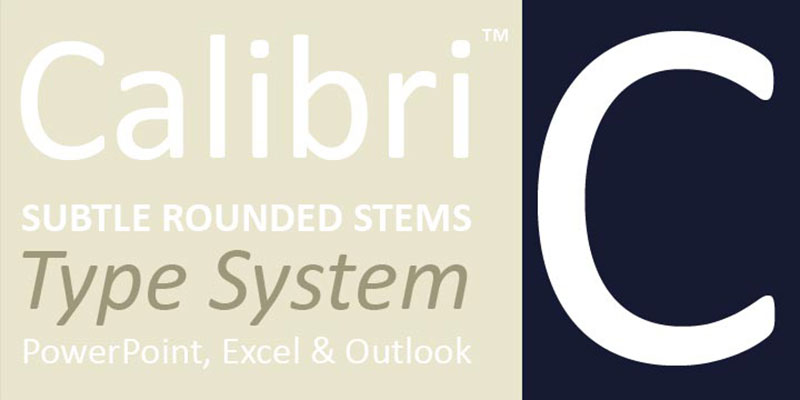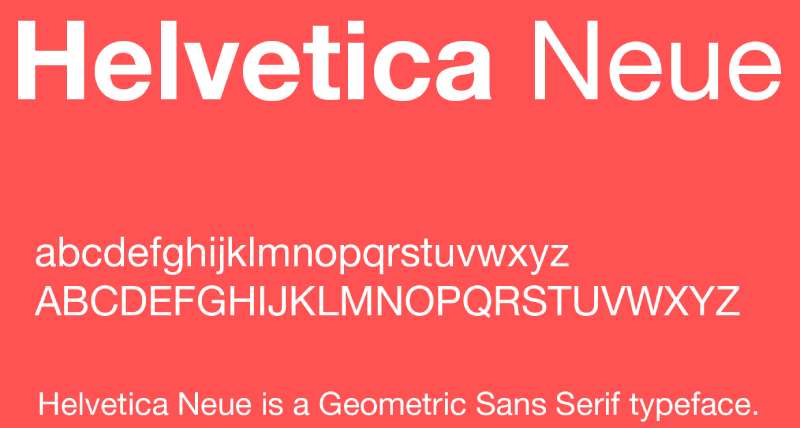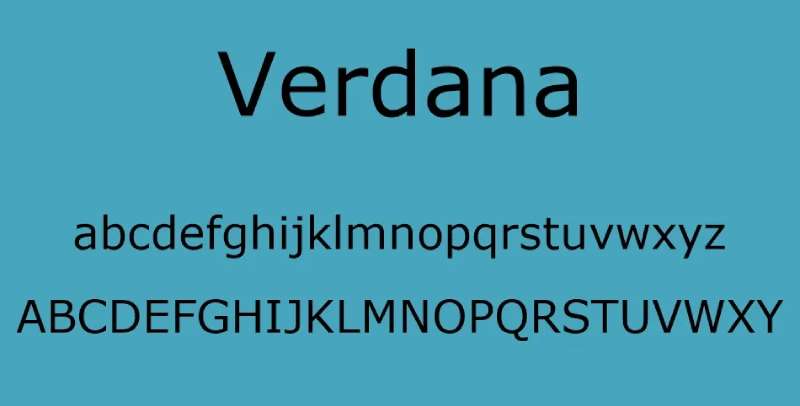
Stellen Sie sich das vor: Sie haben einen Lebenslauf erstellt, der ein Meisterwerk Ihrer Leistungen ist, aber Moment, schreit die Schriftart ‚professionell‘ oder ‚meh‘? Tauchen wir ein in die Welt der besten Schriftarten für Lebensläufe.
Warum? Weil die Schriftart, die Sie wählen, der Anzug ist, den Ihre Worte vor Ihrem zukünftigen Chef tragen. Es geht nicht nur darum, gut auszusehen; es geht darum, diese Worte für Sie arbeiten zu lassen.
In diesem Artikel werden wir die Magie hinter der Auswahl der perfekten Schriftart enthüllen. Es geht nicht nur um Arial gegen Times New Roman.
Es geht um Typografie, die Professionalität vermittelt, Lesbarkeit der Schriftart, die die Augen des Personalvermittlers durch Ihre Fähigkeiten gleiten lässt, und Schriftstile, die Ihre Persönlichkeit widerspiegeln.
Wir führen Sie durch das Labyrinth der digitalen Kompatibilität, stellen sicher, dass Ihr Lebenslauf auf jedem Bildschirm glänzt, und helfen Ihnen, die ATS-freundlichen Wege zu navigieren.
Am Ende haben Sie ein Toolkit aus Serif- und Sans-Serif-Schriftarten, das Kreativität mit Professionalität ausbalanciert.
Sie lernen, wie man Schriftarten für eine visuelle Hierarchie paart, die Schriftgröße für Wirkung anpasst und sicherstellt, dass die Schriftart Ihres Lebenslaufs Personalchef-freundlich ist. Bereit, jeden Buchstaben zu zählen?
Die besten Schriftarten für Lebensläufe
| Schriftartname | Serif/Sans-serif | Lesbarkeit | Professionalität | Häufig verwendet | Einzigartigkeit |
|---|---|---|---|---|---|
| Times New Roman | Serif | Hoch | Sehr hoch | Niedrig |
| Cambria | Serif | Hoch | Hoch | Hoch | Mittel |
| Georgia | Serif | Hoch | Hoch | Mittel | Mittel |
| Garamond | Serif | Hoch | Hoch | Mittel | Hoch |
| Didot | Serif | Mittel | Niedrig | Hoch |
| Book Antiqua | Serif | Hoch | Hoch | Niedrig | Hoch |
| Baskerville | Serif | Hoch | Hoch | Niedrig | Mittel |
| Century Schoolbook | Serif | Hoch | Hoch | Niedrig | Mittel |
| Arial | Sans-serif | Hoch | Mittel | Sehr hoch | Niedrig |
| Calibri | Sans-serif | Hoch | Hoch | Sehr hoch | Niedrig |
| Helvetica | Sans-serif | Hoch | Hoch | Hoch | Niedrig |
| Verdana | Sans-serif | Hoch | Mittel | Hoch | Niedrig |
| Lato | Sans-serif | Hoch | Mittel | Mittel |
| Trebuchet MS | Sans-serif | Hoch | Mittel | Mittel |
| Gill Sans | Sans-serif | Hoch | Mittel | Niedrig | Hoch |
| Futura | Sans-serif | Mittel | Niedrig | Hoch |
| Tahoma | Sans-serif | Hoch | Mittel | Mittel |
Serif-Schriftarten
Hallo! Lassen Sie uns in die Welt der Serifenschriftarten eintauchen, ein Reich, in dem jeder Buchstabe ein wenig mehr Flair bekommt. Wir sprechen über diese kleinen Füße an den Enden der Buchstaben.
Sie sind nicht nur zur Show; sie verleihen Ihrem Lebenslauf ein klassisches, poliertes Aussehen. In einem Stapel von tausend wollen Sie, dass Ihrer flüstert: „Ich bin der Richtige“, oder?
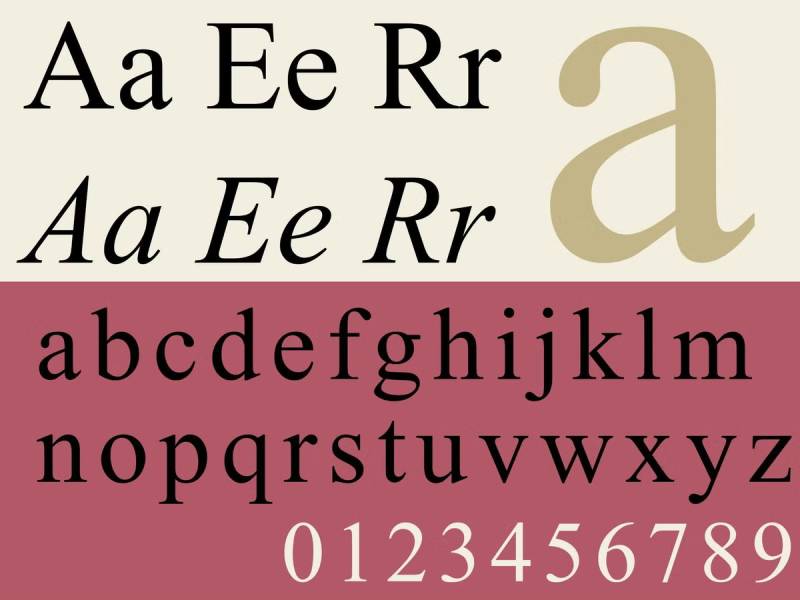
Das mag altmodisch klingen, aber es ist wie das zeitlose kleine schwarze Kleid – es funktioniert einfach. Perfekt, wenn Sie es professionell und lesbar halten wollen. Hier können Sie nichts falsch machen, besonders in formellen Bereichen wie Recht oder Akademie.
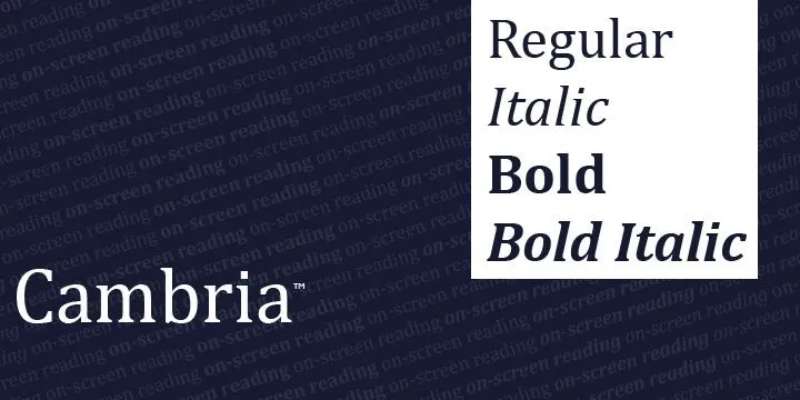
Es ist wie der moderne Cousin von Times New Roman. Speziell für das Lesen auf dem Bildschirm entwickelt, ist seine Lesbarkeit top. Ideal, wenn Ihr Lebenslauf eher auf einem Bildschirm als auf Papier gelesen wird.
Es hat diese warme, einladende Atmosphäre. Seine Buchstaben sind etwas breiter, was es super lesefreundlich macht. Plus, es sieht auf jedem Gerät großartig aus, dank seiner starken digitalen Kompatibilität.
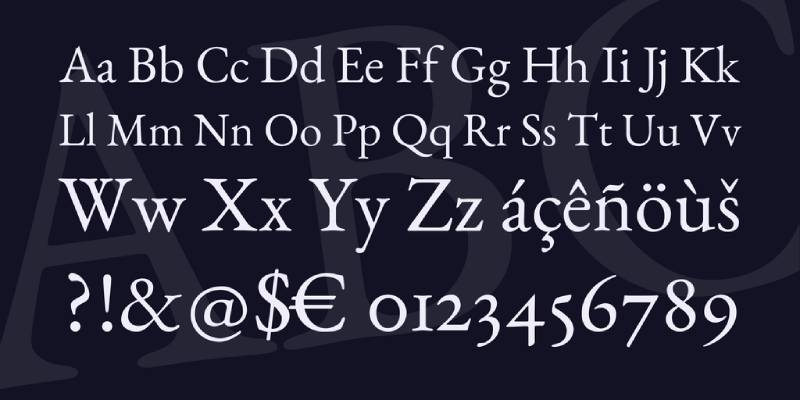
Oh, Garamond – elegant, raffiniert, ein Hauch von altweltlichem Charme. Für diejenigen, die auffallen möchten, aber auf subtile, „Ich habe Klasse“-Art und Weise.
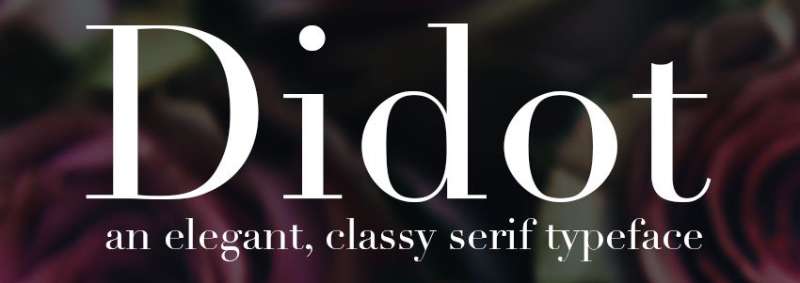
Denken Sie an ein hochwertiges Mode-Magazin. Es ist ziemlich stylisch, also könnte es in kreativeren Bereichen ein Hit sein. Bitte beachten Sie jedoch, dass es besser für Überschriften als für Fließtext ist.
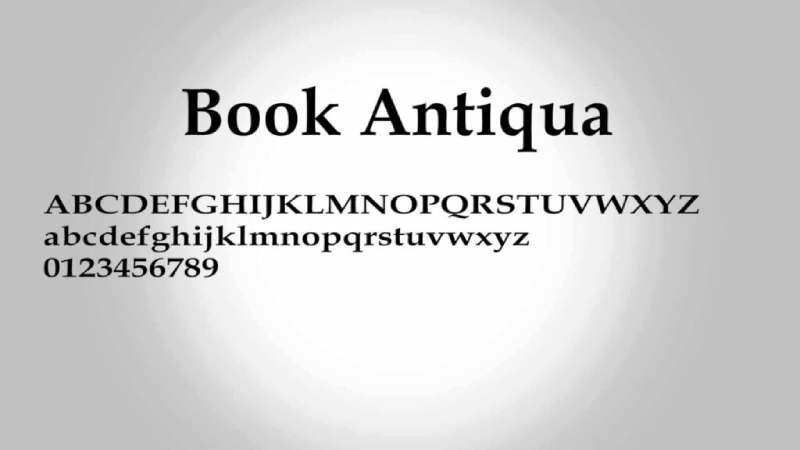
Das ist Ihre Wahl, wenn Sie nach einem klassischen, literarischen Gefühl suchen. Es ist perfekt, um eine Aussage zu machen, ohne um Aufmerksamkeit zu schreien.
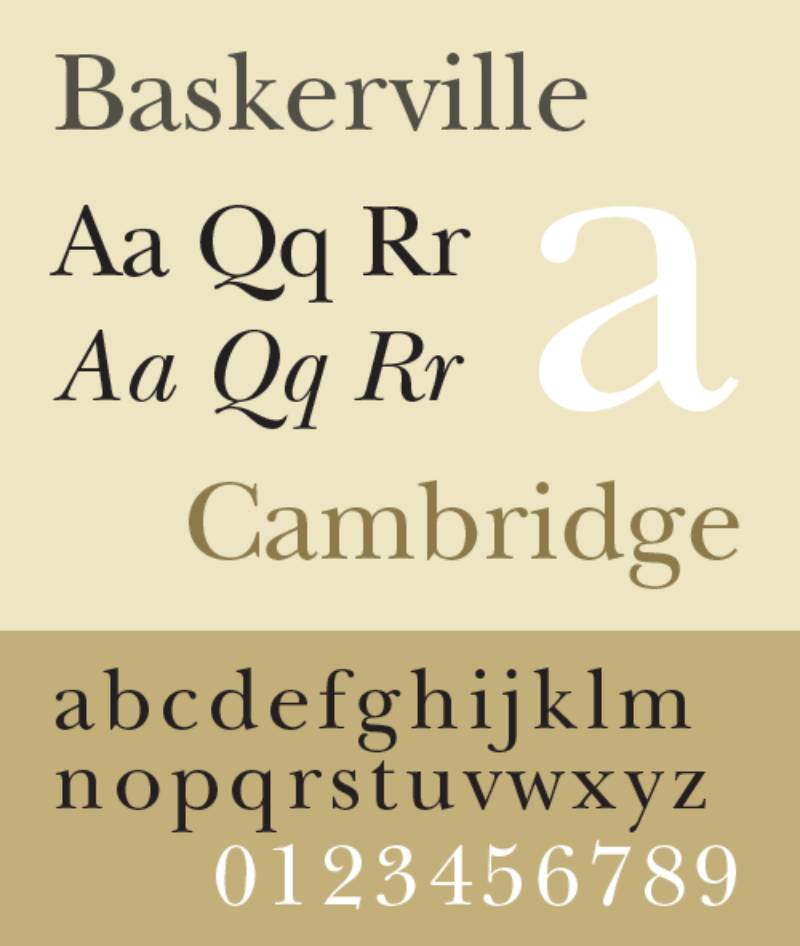
Es hat Geschichte, Qualität und schreit Glaubwürdigkeit. Wenn Sie im Geschäft mit Worten sind, kann diese Schriftart Ihr stiller Verbündeter sein.
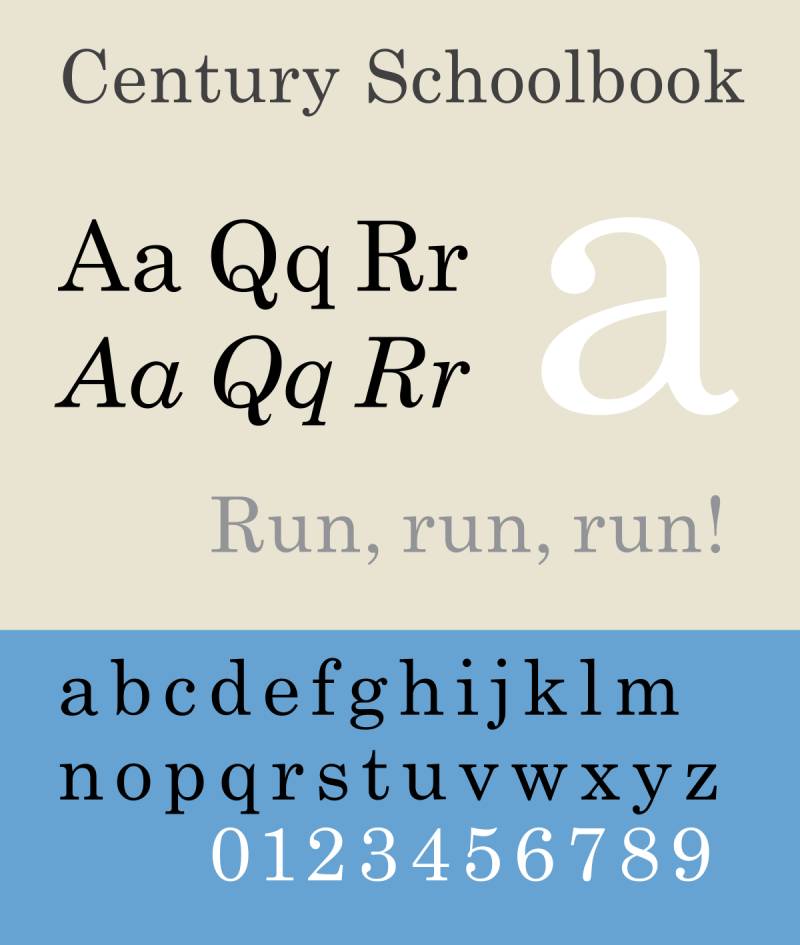
Diese Schriftarten sind alle auf Klarheit und einfache Lesbarkeit ausgelegt. Sie funktionieren großartig für längere Lebensläufe, bei denen Sie den Leser bei der Stange halten möchten.
Sans-Serif-Schriftarten
Okay, wechseln wir jetzt zu Sans-Serif-Schriftarten. Das sind die unkomplizierten, sauberen Charaktere, die auf die kleinen Füße verzichten.
Denken Sie daran als Ihre schlanke, moderne Outfit, das sagt: „Ich bin hier, ich bin klar und ich meine es ernst.“ Perfekt, um Ihren Lebenslauf frisch und aktuell aussehen zu lassen.